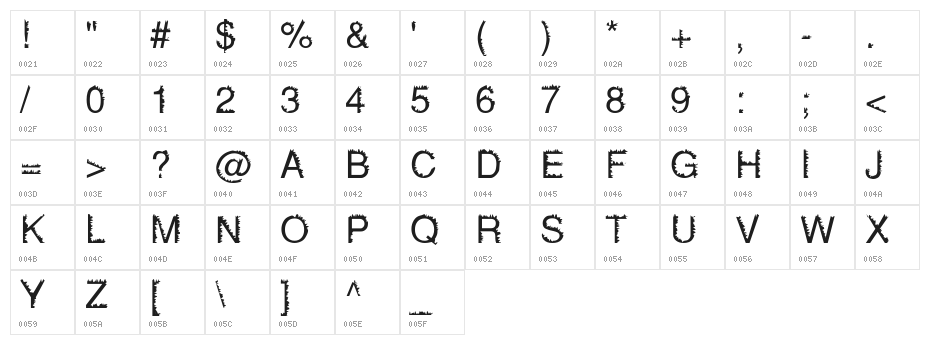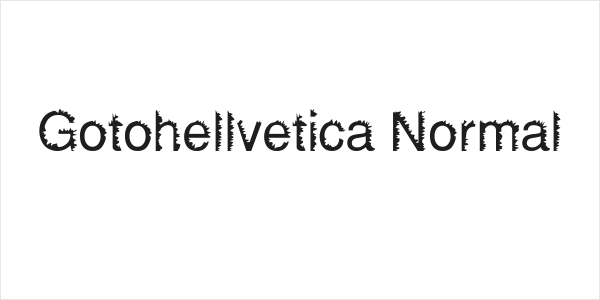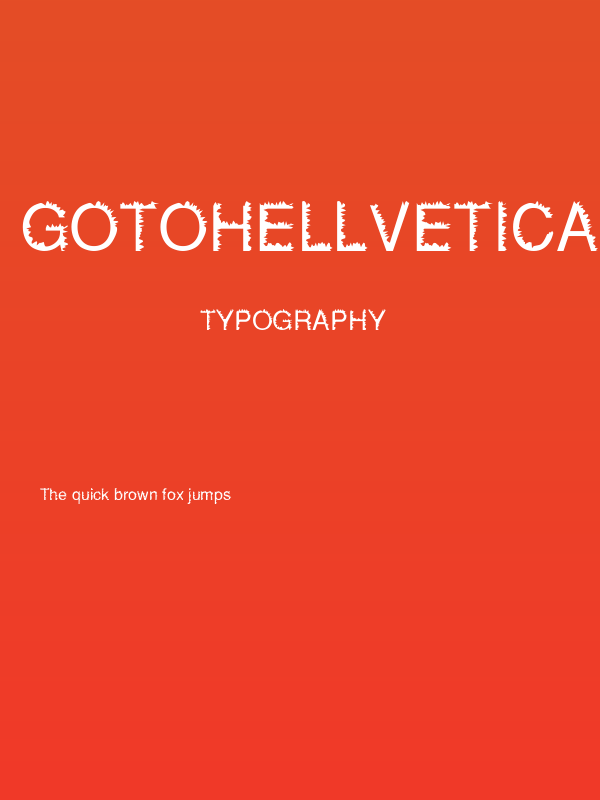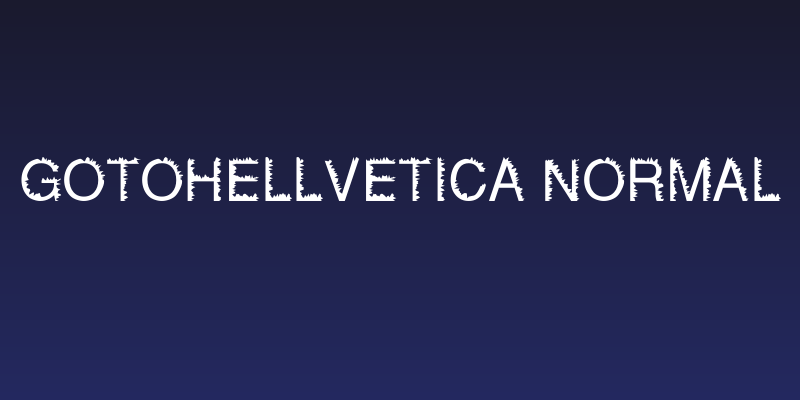
Gotohellvetica Normal Font
| Stile generale | Grunge, Punk, Edgy |
| Caso d'uso | Headlines, Posters, Branding |
| Progetti proposti | Ideal for projects that require a rebellious or edgy theme, such as music album covers, posters, or branding for alternative fashion lines. |